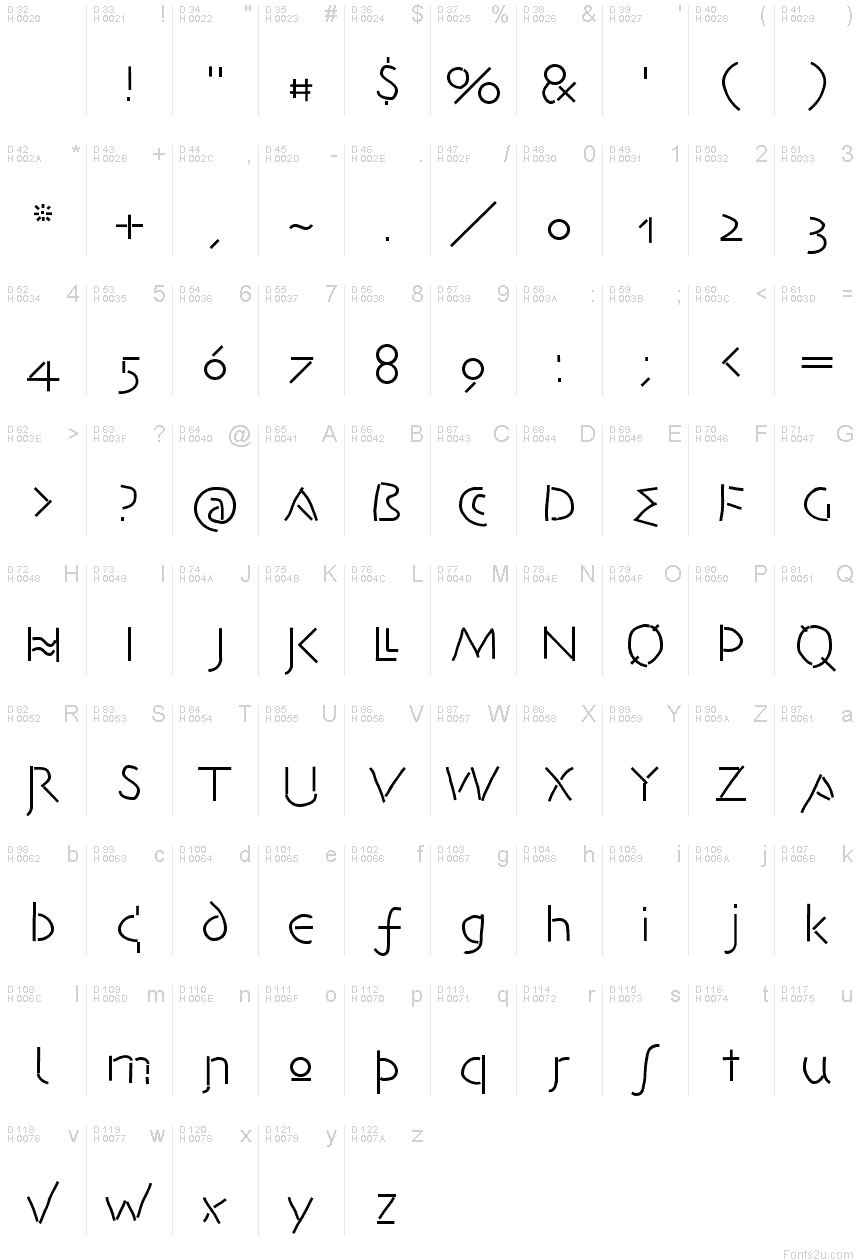
AvantiDilettanti
Nach einem typophilen Schlachtruf \(Slogan\) von Cybapee - als Angrenzung zu den Industrie-Schrifthaendlern von m klein als Skizze am 7.1.2003